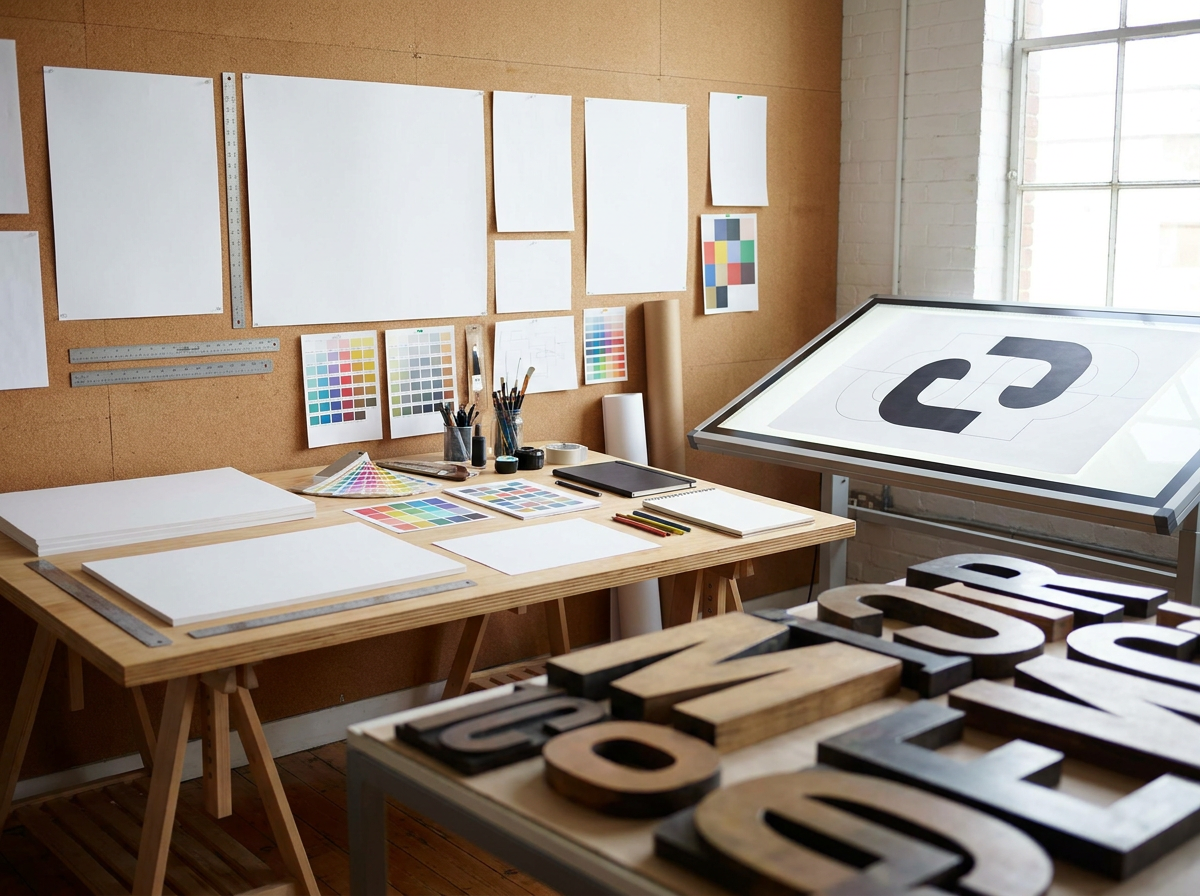
Plakatgestaltung: Welche Schriftarten die Botschaft tragen
Ein Plakat muss innerhalb weniger Sekunden eine Botschaft vermitteln. Doch die visuelle Wirkung hängt nicht allein vom Bildmaterial ab; die Schriftarten für Plakate spielen eine entscheidende Rolle für die Lesbarkeit und die emotionale Ansprache. Eine unpassende Typografie kann die gesamte Werbewirkung zunichtemachen.
Oftmals wird die Wahl der Schriftart unterschätzt, dabei entscheidet sie über die Aufmerksamkeit des Betrachters und die schnelle Erfassbarkeit des Inhalts. Ein Plakat, das nicht sofort verstanden wird, verfehlt seinen Zweck.
Dieser Artikel beleuchtet die Kriterien für die Auswahl effektiver Schriftarten für Plakate, von der psychologischen Wirkung bis zur technischen Umsetzung. Er zeigt, wie sich mit gezielter Typografie die Kommunikationsziele optimal erreichen lassen.
Kurz zusammengefasst
- Die Schriftart beeinflusst maßgeblich die Wirkung und Lesbarkeit von Plakaten.
- Serifenlose Schriften eignen sich oft besser für große Distanzen.
- Kontrast und Schriftgröße sind für die schnelle Erfassbarkeit entscheidend.
- Die Typografie muss zur Botschaft und Zielgruppe des Plakats passen.
Welche Kriterien bestimmen die Lesbarkeit von Plakatschriften?
Die Lesbarkeit von Plakatschriften wird primär durch die Schriftgröße, den Kontrast und die Laufweite der Zeichen bestimmt, um eine schnelle und mühelose Aufnahme der Botschaft aus der Ferne zu gewährleisten.
Ein Plakat ist ein Medium der schnellen Kommunikation. Passanten haben oft nur wenige Sekunden Zeit, die Botschaft zu erfassen. Daher müssen die gewählten Schriftarten sofort ins Auge fallen und ohne Anstrengung lesbar sein.
Die Schriftgröße spielt hierbei eine zentrale Rolle. Eine zu kleine Schrift erfordert eine zu große Nähe, was den Zweck eines Plakats untergräbt. Erfahrungswerte zeigen, dass eine Mindesthöhe von 2,5 cm für den Haupttitel bei einem Betrachtungsabstand von etwa 5 Metern sinnvoll ist.
Der Kontrast zwischen Schrift und Hintergrund ist ebenfalls entscheidend. Helle Schrift auf hellem Grund oder dunkle Schrift auf dunklem Grund erschwert die Erkennung erheblich. Ein starker Hell-Dunkel-Kontrast, beispielsweise Schwarz auf Weiß oder umgekehrt, optimiert die visuelle Trennung der Zeichen.
Praxis-Tipp
Für maximale Lesbarkeit sollte der Kontrastwert zwischen Schrift und Hintergrund nach WCAG 2.1 mindestens 4.5:1 betragen, idealerweise sogar 7:1 für größere Schriftgrade.
Auch die Laufweite, also der Abstand zwischen den einzelnen Buchstaben, beeinflusst die Lesbarkeit. Eine zu enge Laufweite lässt Buchstaben verschmelzen, eine zu weite Laufweite trennt Worte unnötig. Eine ausgewogene Laufweite sorgt für ein harmonisches Schriftbild.
Wie beeinflusst die Schriftfamilie die Fernwirkung?
Die Wahl der Schriftfamilie hat direkte Auswirkungen auf die Fernwirkung und Erkennbarkeit eines Plakats. Serifenlose Schriften wie Helvetica oder Futura sind hier oft im Vorteil.
Serifen, die kleinen Füßchen an den Buchstabenenden, können aus der Distanz verschwimmen und die Konturen der Zeichen undeutlicher machen. Daher eignen sich serifenlose Schriften (Grotesk-Schriften) in der Regel besser für Plakate, da die klaren, schnörkellosen Formen auch aus größerer Entfernung gut zu identifizieren sind.
Schriften mit hoher x-Höhe, also einem großen Verhältnis der Kleinbuchstabenhöhe zur Versalhöhe, verbessern ebenfalls die Lesbarkeit. wirken größer und präsenter, selbst bei moderaten Schriftgrößen.
Welche Rolle spielen Schriftstärke und Schriftschnitt?
Schriftstärke und Schriftschnitt sind entscheidend für die visuelle Hierarchie und die Betonung von Informationen auf einem Plakat.
Eine fette Schriftstärke (Bold oder Black) hebt Überschriften und wichtige Schlagworte hervor. erzeugt eine stärkere Präsenz und zieht die Aufmerksamkeit des Betrachters an. Dünne Schriften hingegen können aus der Distanz schnell verloren gehen.
Der Schriftschnitt, also die Variationen innerhalb einer Schriftfamilie (normal, kursiv, fett), sollte sparsam eingesetzt werden. Zu viele verschiedene Schnitte auf einem Plakat können unruhig wirken und die Botschaft verwässern. Eine Kombination aus einem normalen und einem fetten Schnitt reicht meist aus.
Kurz gesagt: Die Lesbarkeit von Plakatschriften hängt von Schriftgröße, Kontrast, Laufweite und der Wahl einer geeigneten Schriftfamilie ab, um die Botschaft schnell erfassbar zu machen.
Welche Schriftarten eignen sich besonders gut für Plakate?
Für Plakate eignen sich besonders gut serifenlose Schriften mit klaren Formen und guter Lesbarkeit aus der Distanz, wie beispielsweise Helvetica, Futura, Gotham oder Montserrat, da sie eine hohe visuelle Prägnanz aufweisen.
Die Auswahl der richtigen Schriftart ist ein Balanceakt zwischen Ästhetik und Funktionalität. Eine Schrift muss nicht nur gut aussehen, sondern vor allem die Aufgabe erfüllen: die Botschaft klar und schnell zu kommunizieren.
Die Typografie muss stets im Einklang mit der Markenidentität und der Zielgruppe stehen. Eine sorgfältig ausgewählte Schriftart kann die Glaubwürdigkeit einer Marke stärken, Emotionen wecken und die gewünschte Botschaft effektiv transportieren. Fehler in der Schriftwahl hingegen können die gesamte Werbewirkung zunichtemachen.
Letztlich ist die Schriftwahl für Plakate eine Investition in die Effektivität der Kommunikation. Eine fundierte Entscheidung, die alle relevanten Faktoren berücksichtigt, zahlt sich in einer höheren Aufmerksamkeit und einer klareren Botschaft aus.